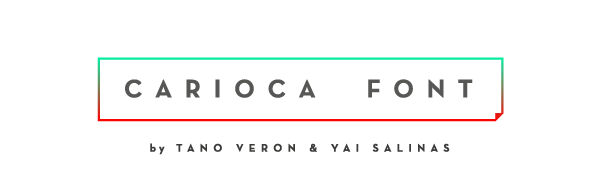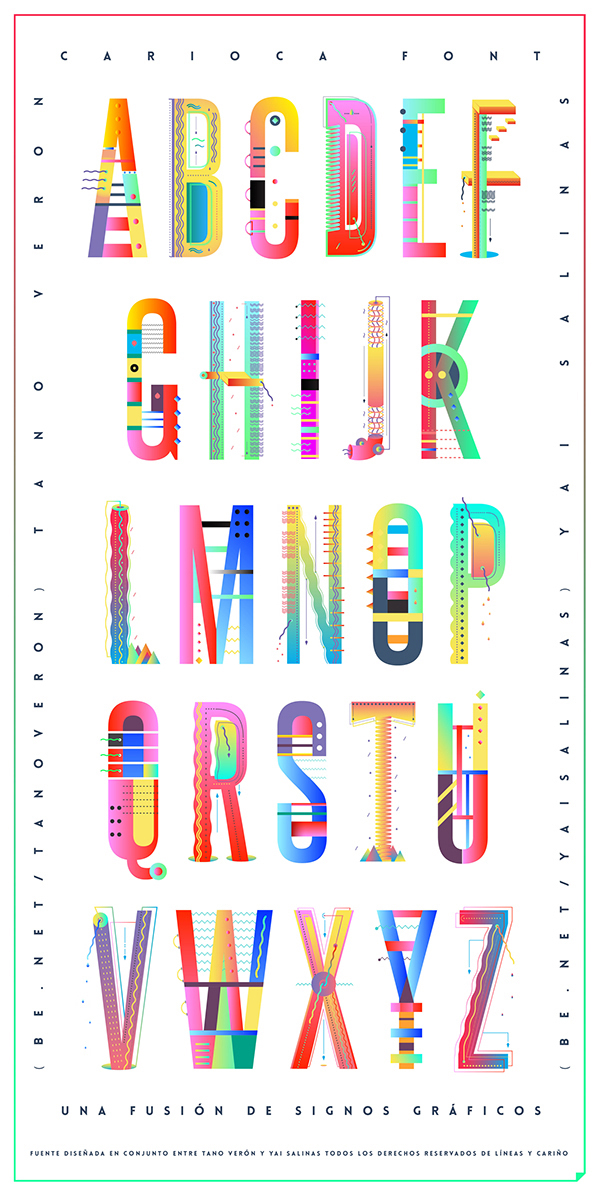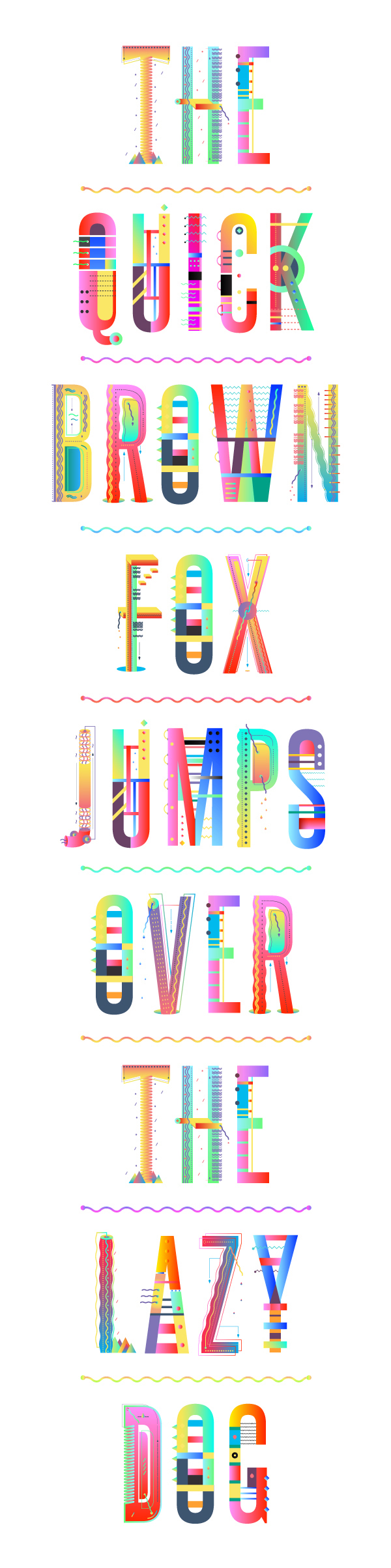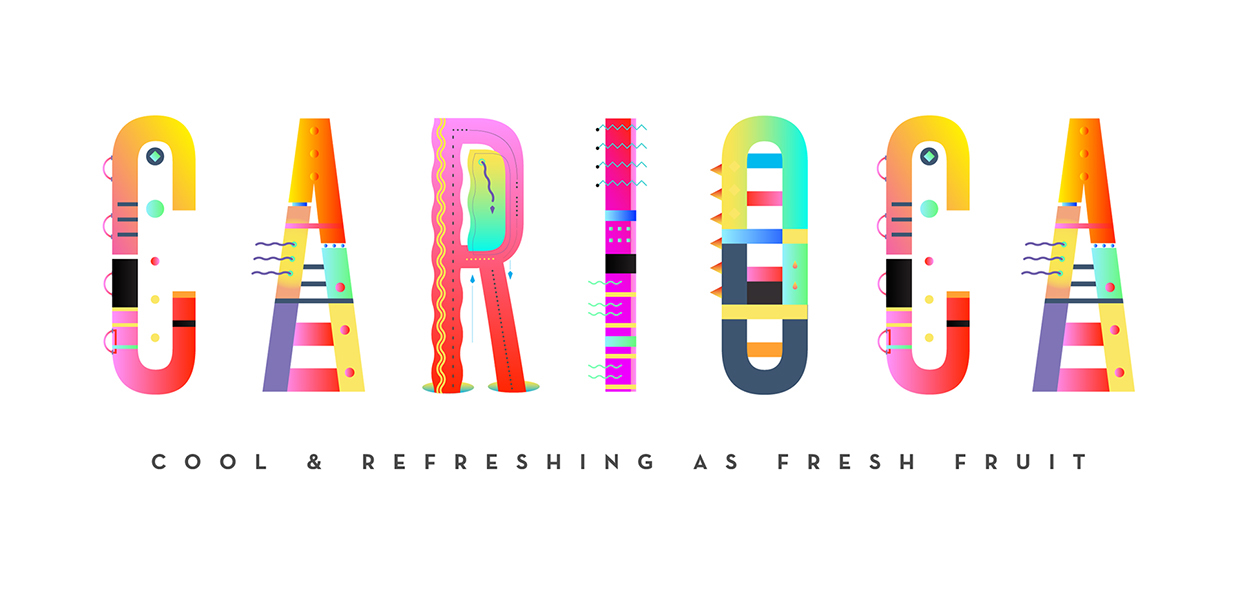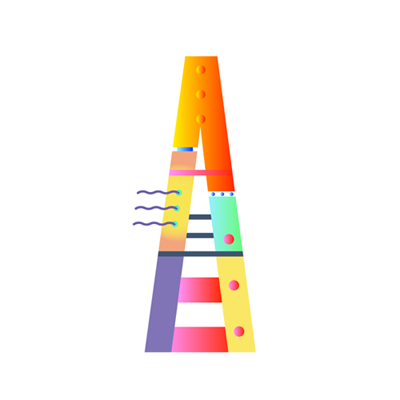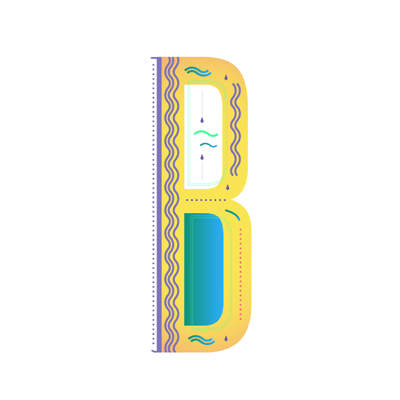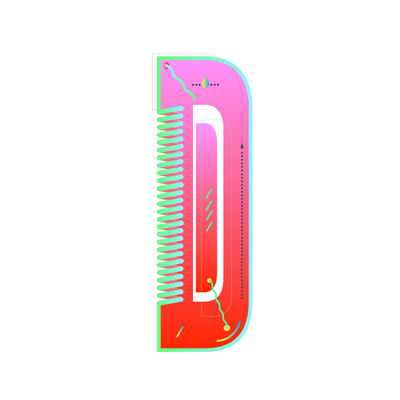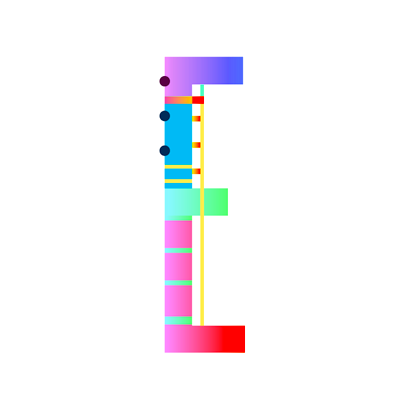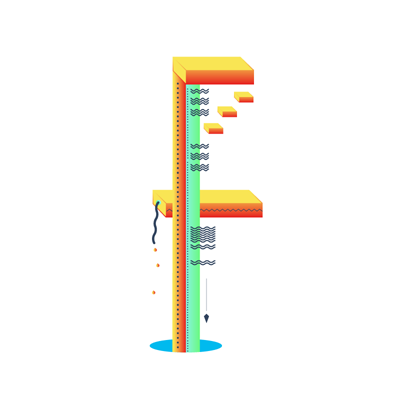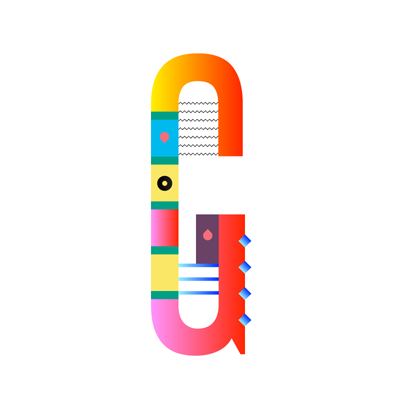
Yay! Hôm nay đã là thứ 7 rồi, đã tới lúc cho phép mình ngủ nướng và relax sau một tuần “bão não” căng thẳng với nhiều dự án cuối năm. RGB.vn muốn chia sẻ với các bạn đì zai nờ một font chữ rất độc đáo và khá nghịch ngợm của nhà thiết kế TANO VERON & YAI SALINAS. Mọi người download từ link phía dưới nhé.